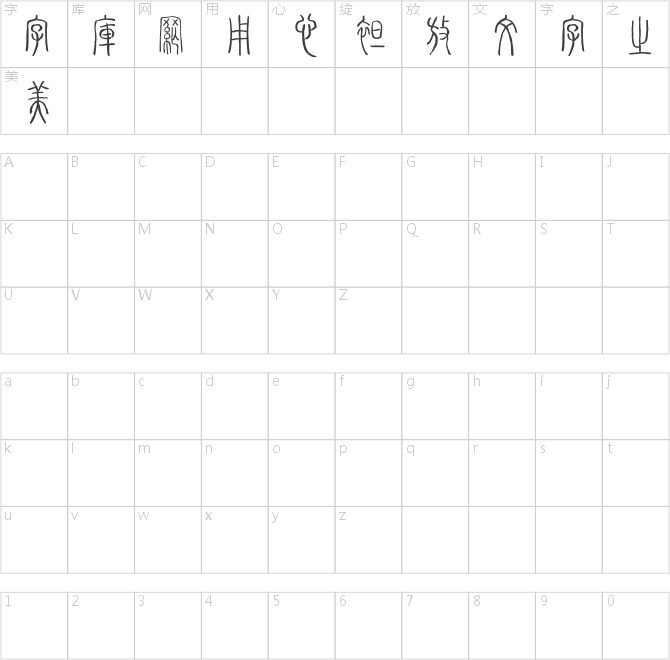
李親湖
李親湖 ,廣東省榮譽(yù)市民,中國文學(xué)藝術(shù)界聯(lián)合會(huì)名譽(yù)主席,廣東省文學(xué)藝術(shù)界聯(lián)合會(huì)終身名譽(yù)主席,廣東省政協(xié)書畫藝術(shù)交流促進(jìn)會(huì)會(huì)員,法蘭西皇家美術(shù)學(xué)院皇家首席藝術(shù)家,加拿大阿爾伯塔大學(xué)榮譽(yù)博士學(xué)位,南粵文化之星,共和國杰出功勛文化藝家,中國文藝復(fù)興百杰人物。
李親湖篆體字庫的字長方偏瘦形,每一字端正,中鋒用筆,筆畫橫平豎直,圓勁均勻,粗細(xì)一致,畫與畫、豎與豎之問等距平行,隨意起隨意收,方中寓圓結(jié)字左右對(duì)稱,上下對(duì)稱,圓弧形筆畫左右傾斜度的對(duì)稱,上緊下松,美態(tài)多姿,仔細(xì)品嘗味道濃濃。視覺效果強(qiáng)烈地沖擊著眼球,讓品嘗者神游其間、沉醉于中。